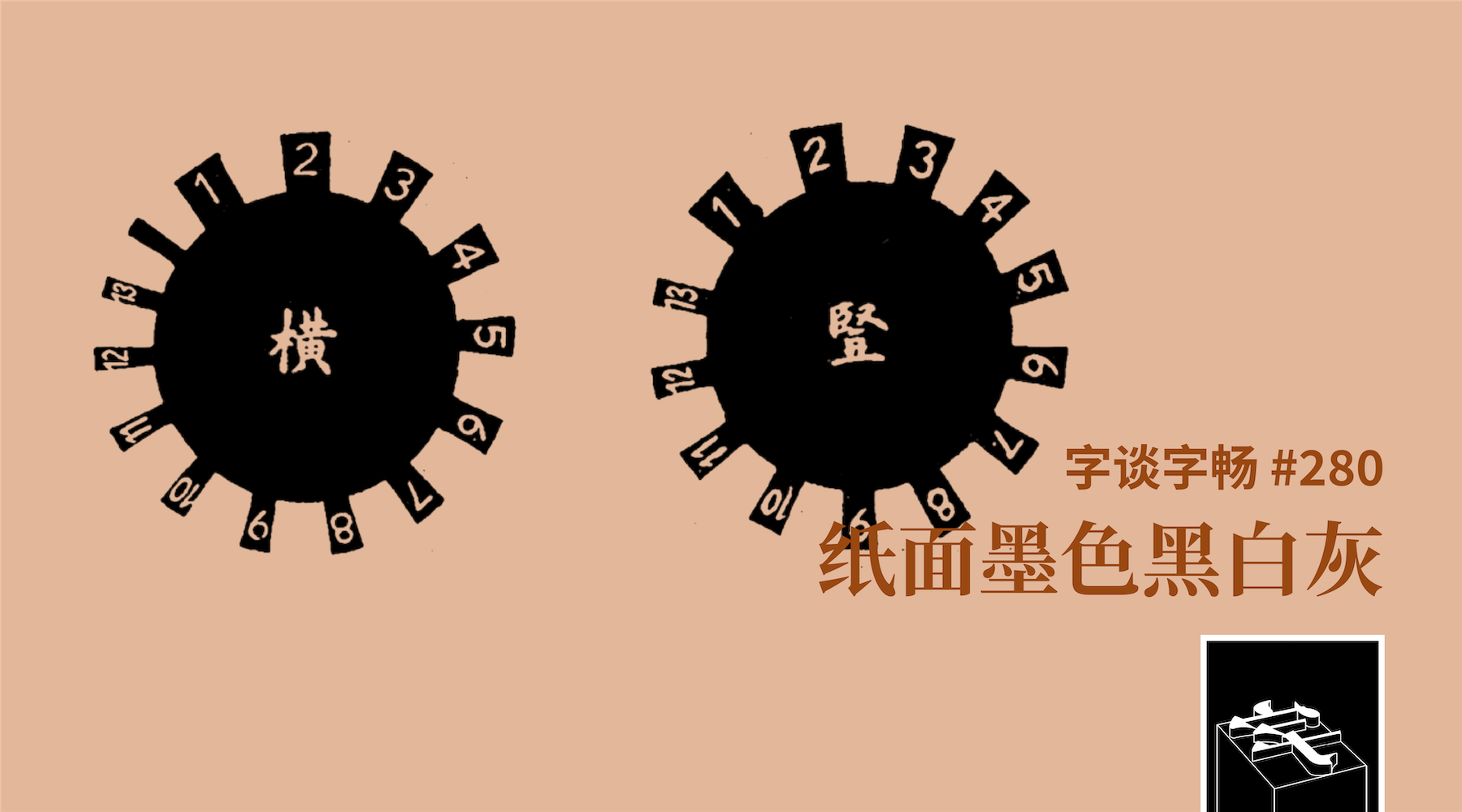
本期节目,老朋友厉致谦与我们一起探讨中文字体设计中的「黑度/灰度」概念,辨析这一概念的术语用词、设计原理以及各家前辈的实践方法。
- Color,字体排印术语,常译作「灰度」
- 夏征农(编).《辞海》(1989 年版).上海辞书出版社,1989 年
- 徐學成(著).厲致謙、應寧(編著).《字耕一生:徐學成的故事》.三聯書店(香港)有限公司,2026 年
- 徐学成,字体设计师,早年于上海印刷技术研究所;「汉字印刷字体书写技艺」(上海市非物质文化遗产项目)代表性传承人
- 今井直一(1896—1963),日本印刷技师,曾任三省堂社长、日本印刷学会会长,著有《书籍与活字》(『書物と活字』)